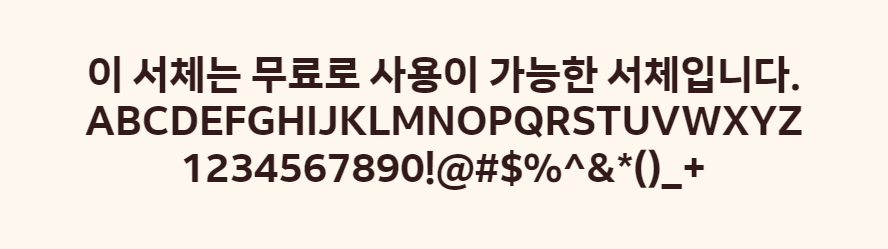
나눔휴먼
폰트 제작 배경
나눔휴먼 폰트는 일상에서 자연스럽게 사용할 수 있는 서체를 제공하기 위해 개발되었습니다. 네이버는 '한글한글 아름답게' 캠페인의 일환으로, 디지털 환경에서도 가독성이 높고 친근한 인상을 주는 글꼴을 제작하고자 했습니다. 이를 통해 사용자들이 다양한 매체에서 편안하게 활용할 수 있는 서체를 제공하고자 하였습니다.
폰트 디자인의 특징
나눔휴먼은 손글씨의 부드러운 느낌이 담긴 고딕체로, 직선의 간결함과 곡선의 부드러움이 조화를 이루어 따뜻함을 전하는 글꼴입니다. 이러한 디자인은 제목과 본문 모두에 어울리며, 다양한 굵기를 제공하여 활용성을 높였습니다.
폰트 사용 용도
이 폰트는 제목과 본문 모두에 사용할 수 있는 휴머니스트 계열의 글꼴로, 웹사이트, 포스터, 카드 뉴스, 프레젠테이션 자료 등 다양한 디자인 요소에 활용할 수 있습니다. 특히, 감성적인 분위기를 강조해야 하는 콘텐츠나 부드러운 이미지를 전달하고 싶은 경우 더욱 효과적입니다.
폰트 미리보기